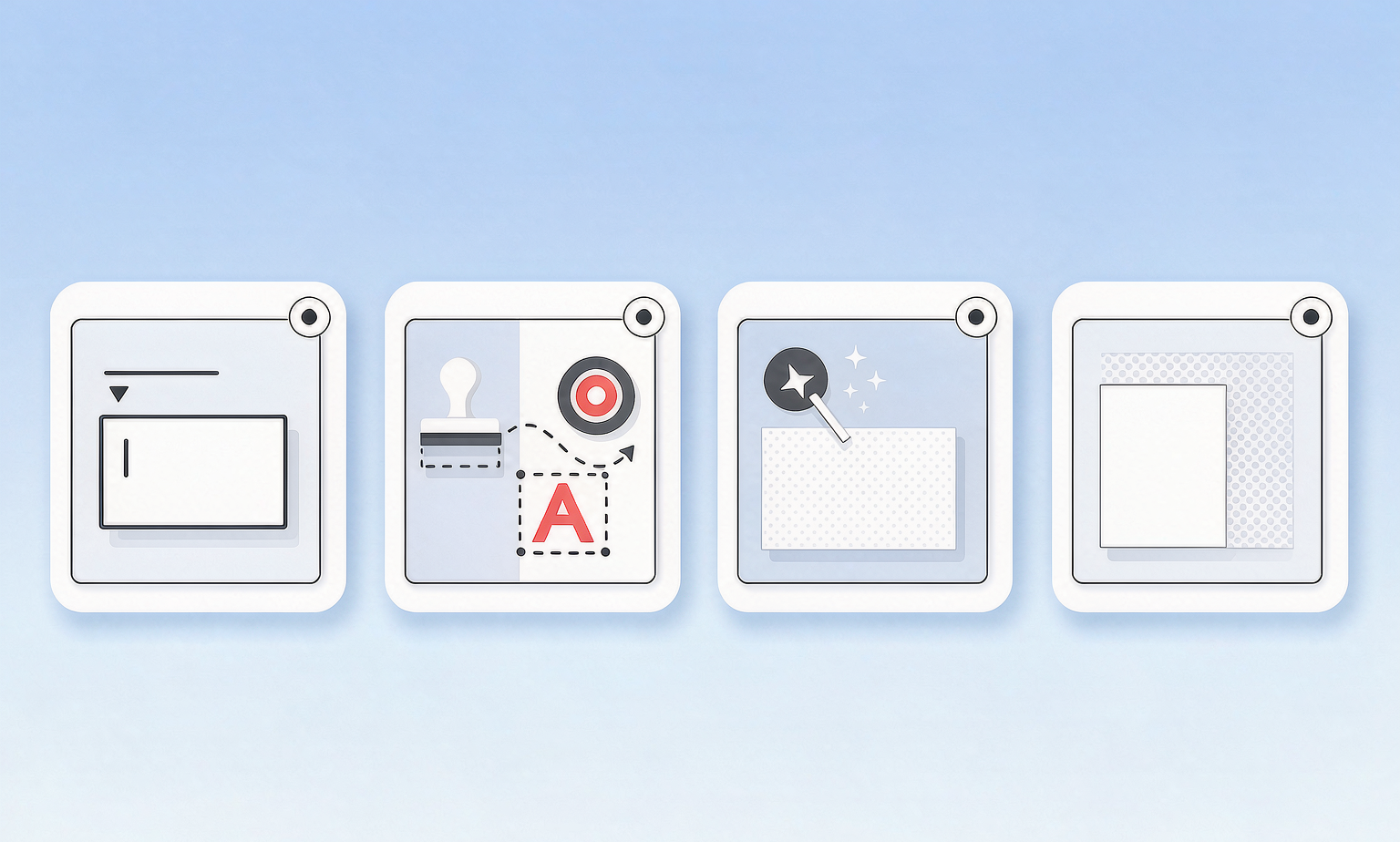
PS改字怎么弄?改完与原图字体一模一样,无痕不穿帮
做电商主图、活动海报的时候,PS改字是绕不开的活:改价格、改卖点、改活动时间,一天十几张很正常。难点从来不是把字打上去,而是改完看不出改过——字体差一点、颜色偏一点、边缘带点毛边,客户一眼就能看出”这张图是P的”。
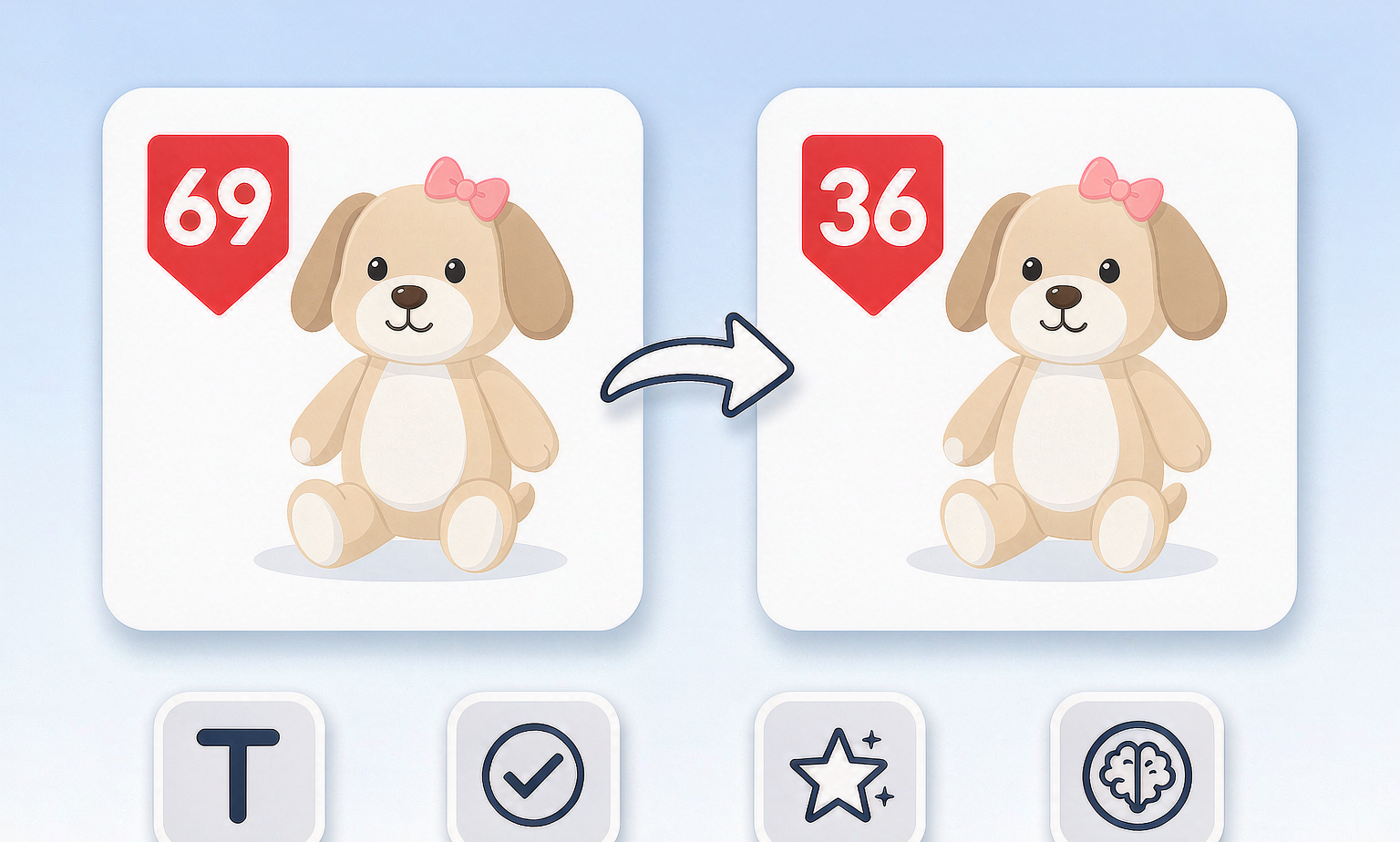
PS改字效果对比图,左侧商品海报红色价签写着69,右侧同一张海报价签改成36,中间用箭头连接,底部四个图标分别代表文字工具、修补去字、内容识别填充、AI一键改字,浅蓝色渐变背景
下面按动手顺序讲:改字前要确认的3件事 → 4种手工改字方法 → 更省事的一键改字方案。
一、动手前先确认这3件事
很多人改字失败不是手法问题,是方向错了。
1. 分层PSD,还是合成图片
• 分层PSD源文件:文字还是独立图层,双击就能改,字体、颜色、描边全在,无痕无损。
• 合成图片(JPG/PNG):文字已经和背景焊在一起,必须先去掉旧字再重新打字,大多数人就是卡在这一步。
能拿到源文件,就别硬P。
2. 字体认对,成功一半
原图用的思源黑体 Heavy,你拿系统默认的雅黑去顶,骨架都不一样,怎么可能像。
3. 颜色、光影、锐度要对齐
• 颜色:别用吸管只点一下,文字各位置明暗不同,要取平均值
• 光影:原字有投影、内阴影、外发光,新字也得有,方向和参数都要对上
• 锐度:原字清晰,新字发虚就像贴纸浮在上面
二、普通PS改字的4种方法
PS改字四种方法示意图,四个并排面板分别代表文字图层直接编辑、修补工具去字、内容识别填充、色块覆盖换字
下面4种覆盖绝大多数场景,按图片类型对号入座。
方法一:文字图层直接编辑(有PSD源文件)
适用:保留了文字图层的 PSD 源文件,模板改字首选。
步骤:图层面板找到带”T”的文字图层 → 用横排文字工具(快捷键 T)点中文字 → 全选删掉输入新文案,字体、字号、颜色、描边自动继承。
优点:无痕无损,10 秒搞定。缺点:必须有源文件,别人发你的 JPG 走不通。
方法二:修补工具(纯色 / 简单背景)
适用:纯色底、简约渐变底的成品图。
步骤:【修补工具】+ 属性栏选【源】模式 → 圈选要删的文字(贴紧边缘)→ 把选区拖到旁边干净的背景处松手,PS 自动匹配填充 → Ctrl+D 取消选区,在原位置打上新字。
坑点:文字压在渐变上容易出色块断层,要多修几次。
方法三:内容识别填充(复杂纹理背景)
适用:背景有纹理、有场景元素、有光影叠加的海报。
步骤:套索工具圈选文字区域(边缘留 1–2 像素余量)→【编辑】→【内容识别填充】→ PS 自动分析周边纹理、光影生成填充,可用画笔涂抹不准的区域让它重算 → 确认后向下合并新图层,重新打字。
坑点:文字跨在两种材质上(一半在产品、一半在背景)会糊,要手动分区处理。
方法四:色块覆盖 + 重新打字(纯色标签)
适用:文字在纯色标签、色块横幅上。
步骤:矩形选框框住整个标签 → 吸管取标签底色,Alt+Delete 填充覆盖旧字 → 打上新文字,用【对齐】工具居中。
优点:快,几乎不出错。缺点:只适合纯色块,稍微有点拉丝、渐变、噪点就露馅。
三、想让新字和原图一模一样,还要调这些
字体识别:3个免费办法
• 求字体网 / 识字体网:上传局部文字截图,自动匹配字体名称
• 看图归类:中文无非黑体、宋体、圆体几大类,先定大类再缩范围
• PS 自带匹配:用选框选中文字区域,菜单【文字】→【匹配字体】
字距、行距、基线
• 字间距:偏松或偏紧都要微调到视觉一致
• 行距:多行文字必须调,否则一眼看出是两拨
• 基线:文字高度要一致,不能一个高一个低
描边、阴影、模糊
原字有描边就加【描边】,有投影就加【投影】并调角度、距离、大小;原字略虚,给文字加 0.3–0.5 像素高斯模糊,反而更真实。
变形与透视
文字在易拉罐、包装盒这类曲面上时,直接打字会”平”,得用【编辑】→【变换】→【变形 / 透视】掰成贴合曲面的弧度。这步纯手工,也最耗时。
四、更省事的做法:用 StartAI 的 Banana 修图
上面这套流程走下来,熟练的设计师一张图也要十几分钟,一天几十张真的扛不住。
这也是为什么越来越多电商设计团队开始用 StartAI——一个直接嵌在 Photoshop 里的 AI 插件,不用切换软件、不用导出图片,改字在 PS 里就能闭环。里面最适合改字的是 Banana 修图:不用抠选区、不用修补工具、不用翻字体库,把要改的图传进去,用一句话说清”哪个字要改成什么”就行。
核心句式其实就一句:
把图中文字”XX”改成”XX”
它把手工的4步,合成了一句话
手工改字要拆成四步:擦掉旧字 → 修好背景 → 打上新字 → 对光影字体。Banana 修图把这四步收进一句话:
• 不用抠选区、不用擦字补背景:直接把图载进插件,它自己定位文字,擦除时把被挡住的纹理、光影一并补回来
• 不用翻字体库:按原图风格生成,字重、粗细、颜色都往原图靠
• 不用手工回填:结果直接落回 PS 图层原位
StartAI PS插件面板的AI功能列表,红框标出 Banana修图 V3 入口,同屏还有 GPT生图、AI图层拆分、AI高级修图、AI商品图、图片去水印、AI换色等功能
具体操作:3步走
第一步,调出面板:在 PS 里打开要改的图,菜单【窗口】→【增效工具】→【StartAI】,「AI功能」默认就是 Banana修图 V3。
第二步,载入原图:点「原图」区域的加号把图片载进去(最多 5 张,长按可拖拽排序)。
第三步,写需求,点生成:在「修图需求」框里写清要改什么,比如”帮我把限时特价69元改为限时特惠36元”,模型选 专业版Pro、分辨率选 4K,勾上「完成图贴回选区」,点【立即生成】。等十几秒,AI 自动完成”删旧字 → 修背景 → 匹配字体颜色 → 放新字”,结果直接贴回 PS 原位。
StartAI Banana修图实际操作界面,修图需求框写着「帮我把限时特价69元改为限时特惠36元」,修图模型选专业版Pro、分辨率选4K、完成图贴回选区已开启,右侧为生成好的限时特惠36元海报
可以照抄的改字提示词
写提示词的关键,是把 位置风格 说清楚。下面几条可以直接套:
1. 基础版:把图中文字”限时特价69元”改成”限时特价36元”
2. 保样式版:把图中文字”2025新品”改成”2026新品”,字体、颜色、大小、位置与原图保持一致
3. 多文字版:把”满199减50″改为”满299减100″,把”活动时间:9月1日—9月10日”改为”活动时间:9月20日—9月30日”
4. 复杂背景版:把”XX旗舰店”改成”YY官方旗舰店”,保持背景纹理和光影自然,字体风格与原图一致,不要有修改痕迹
原图字体比较特殊时,直接在提示词里写明风格,比如”用黑体””保持手写体感觉”,AI 会往这个方向匹配。
五、普通PS改字 vs StartAI Banana修图
对比项普通PS手工改字StartAI Banana修图
有PSD源文件很快,直接改图层同样支持,不必依赖源文件
只有JPG/PNG成品图需要修补或内容识别,慢载入图片 + 一句话提示词
复杂纹理背景容易出色块、断层自动匹配背景纹理光影
字体匹配手动识别、逐个试按原图风格生成,字重颜色自动贴合
单张耗时10–30 分钟10–30 秒
批量改图时间线性叠加载图—写提示词—生成,流水线操作
上手门槛需要 PS 功底会打字就会用
六、常见问题
Q1:PS改字怎么弄最简单?
有 PSD 源文件就直接在文字图层改,最简单也无痕。只有 JPG 的话,用 Banana 修图一句话改完;手工路线也能做,但要一张张处理。
Q2:改完和原图字体不一样怎么办?
先用识字体工具或 PS 的【匹配字体】确定原字体,确认不了就找骨架最接近的替代,再把字距、行距、描边、阴影逐项对齐。骨架差距太大时,直接用 Banana 修图重绘文字区域,提示词里写明”字体风格与原图一致”。
Q3:怎么把文字去掉又不伤背景?
纯色背景用修补工具,复杂纹理用内容识别填充;压在产品和材质上的文字,推荐用 Banana 修图,它擦除文字的同时会按周边像素补全背景,比手动修补干净。
Q4:PS改的字会不会被看出来?
最容易穿帮的是三种情况:字体骨架不对、颜色明暗不一致、边缘没有做融合。这三点做到位,普通人基本看不出来。
七、总结
PS改字的难点从来不是”会不会打字”,而是去字要干净、新字要像
• 有源文件 → 文字图层直接改,最快;纯色背景 → 修补工具 / 色块覆盖
• 复杂纹理 → 内容识别填充,或 Banana 修图一句话搞定
• 想让新字和原图一模一样 → 字体、字距、描边阴影、变形,一项都不能少
• 想省时间、尤其批量改图 → 用 StartAI 的 Banana 修图,载图—写提示词—生成
改字这种重复度高又抠细节的活交给 AI,省下来的时间用在创意和排版上更划算。